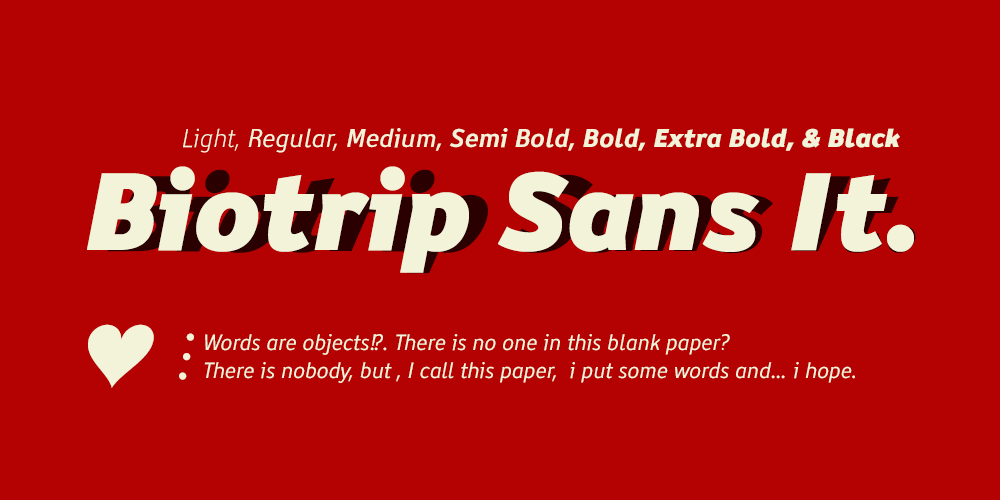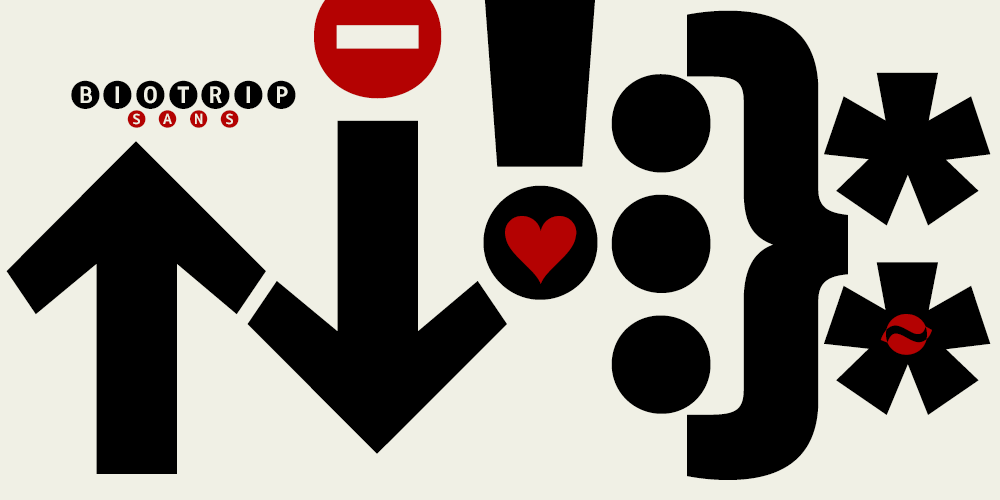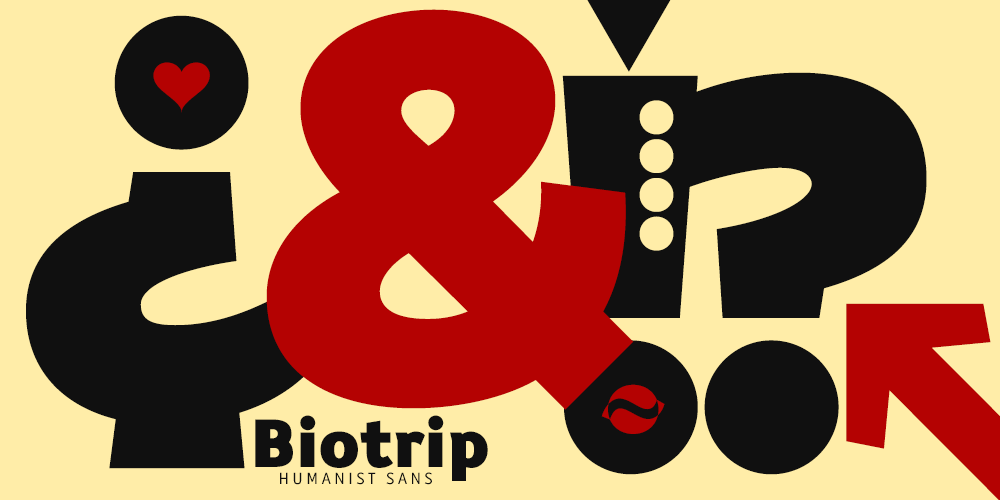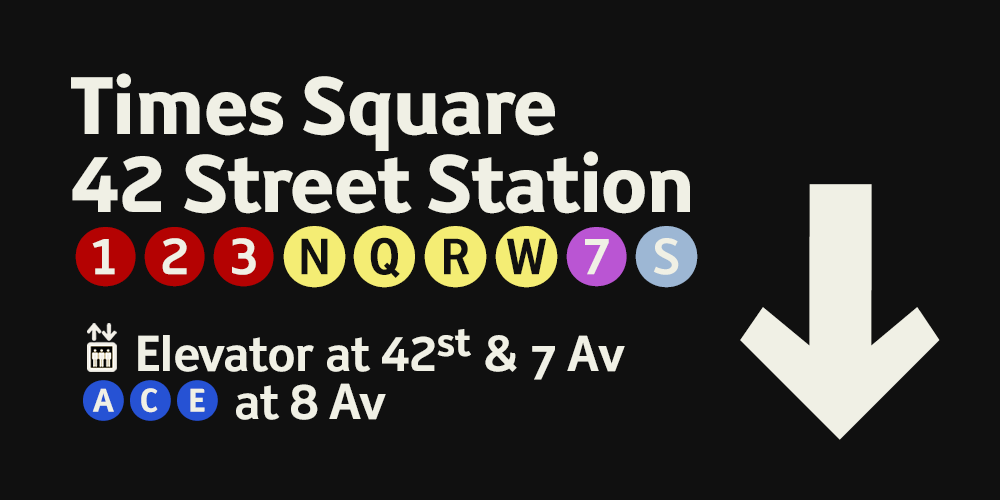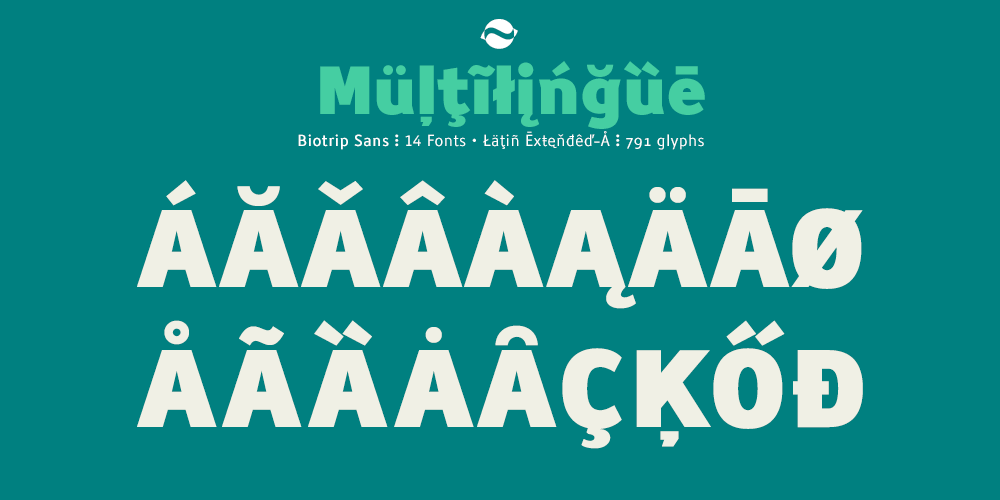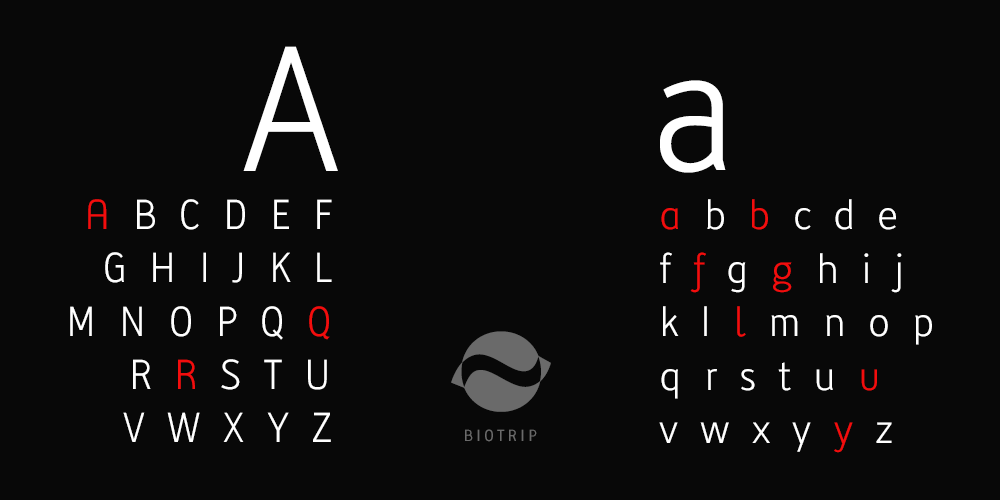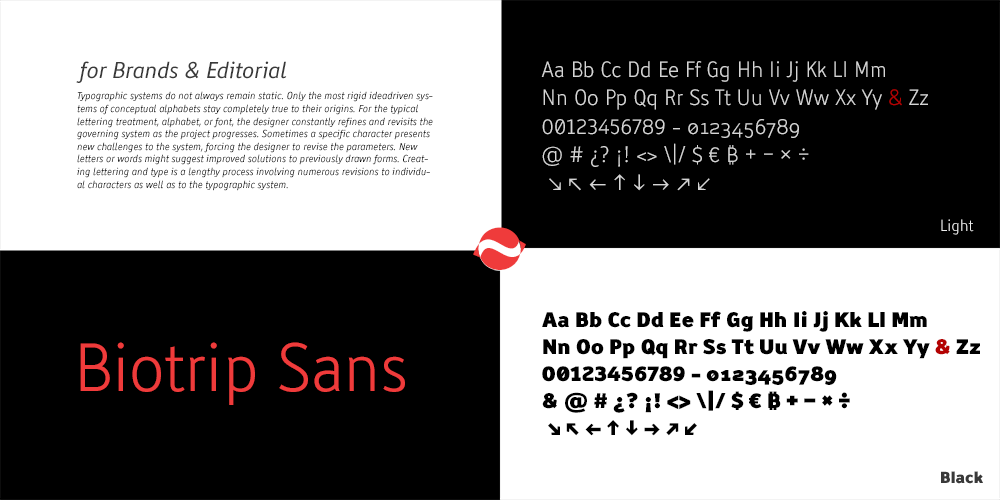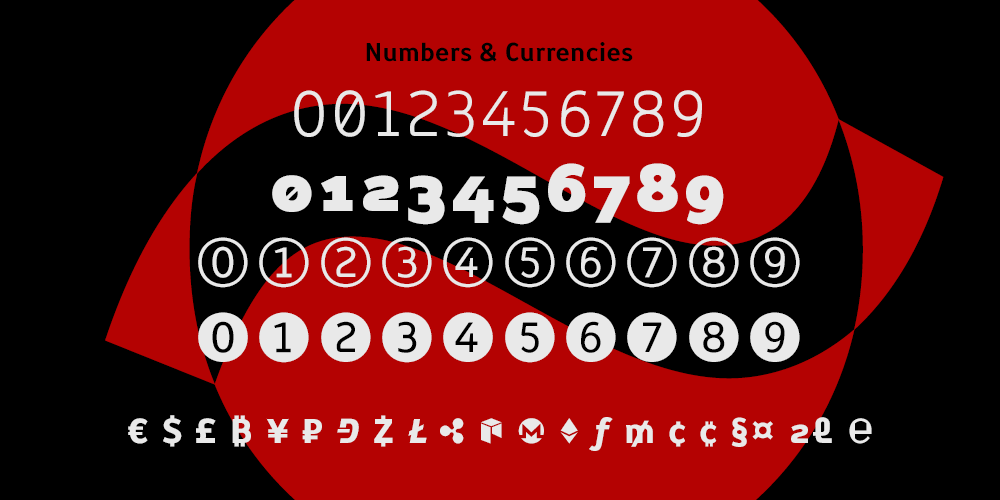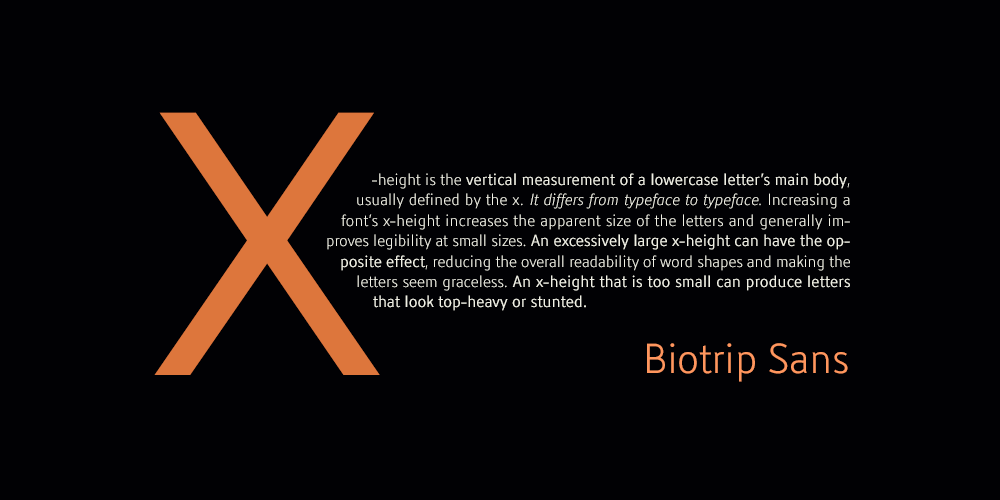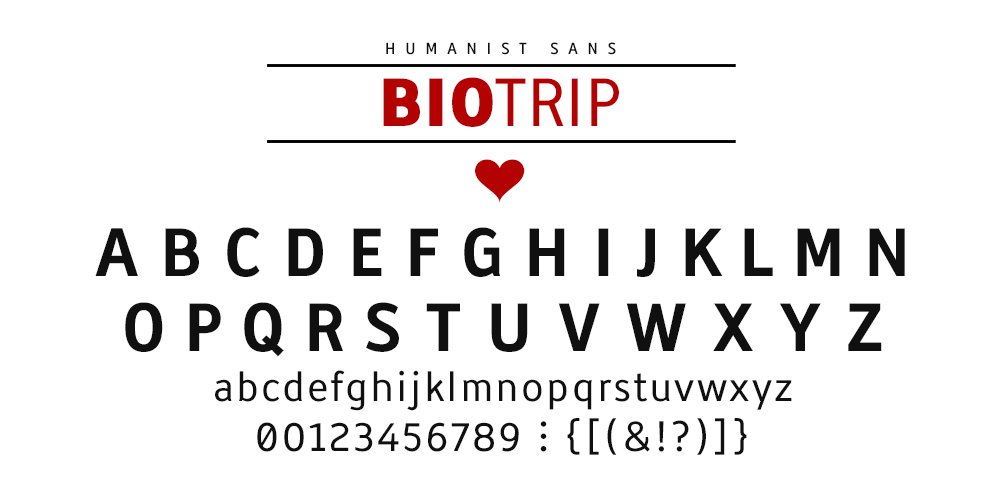
Estilo: Sans Serif, Display, Humanista, Editorial, Branding
Proporción: Light, Regular, Medium, Semi Bold, Bold, Extra Bold, Black
Glyphs: 791
Alternates: 189
Latin-Extended: Latín Básico, Europa Occidental, Central & Oriental.
Autor: deFharo
Versión: 1.791
Año de publicación: 2025.
Funciones OpenType: Additional languages, All Alternates, Alternate Annotation Forms, Bitcoin, Capital Spacing, Contextual Alternates, Denominators, Discretionary Ligatures, Fractions, Historical Forms, Inferiors, Kerning, Localized Forms, Numerators, Oldstyle Figures, Optical Size, Ordinals, Scientific Inferiors, Slashed Zero, Standard Ligatures, Stylistic Set, Subscript, Superior letters, Superiors, Superscript.
Regular & Italic | 791 glyphs | 14 fonts
Biotrip Sans — una tipografía que respira
He dado vida a una familia tipográfica amigable que es, ante todo, un viaje. Un viaje (Trip) desde la pureza de la geometría hacia la calidez de lo orgánico (Bio).
He diseñado Biotrip Sans desde ese punto de equilibrio imposible entre la razón y el impulso, entre la línea precisa del vector y el trazo impredecible de la mano. Es una sans humanista, una categoría que vive en ese fascinante borde donde lo geométrico se ablanda, donde las proporciones racionales ceden espacio a la humanidad del gesto. Aunque su estructura parte de la geometría, su espíritu es orgánico, vivo. No hay rigidez mecánica aquí, ni la frialdad de las fuentes grotescas. Cada curva fue pensada para ser vivida, no solo leída.
Biotrip Sans nace del trazo vivo, del impulso que une la mente al movimiento. Su estructura parte de la geometría, sí, pero cada forma fue suavizada por un pulso orgánico que hace que el ojo humano confíe, lea, respire. Las formas abiertas y neutrales y el ritmo equilibrado la convierten en una fuente cálida, versátil y naturalmente legible, incluso en los tamaños más pequeños —porque los buenos textos no deberían gritar para ser entendidos.
Una familia con vocación expansiva
Biotrip Sans se despliega en 14 fuentes metódicamente diseñadas, distribuidas en 2 estilos (Regular e Itálica genuina y fluida) y 7 pesos que van desde la elegancia etérea del Light hasta el impacto contundente del Black. Una familia grande, sí, pero no dispersa: cada peso comparte la misma tensión entre la estructura y la fluidez, entre la precisión tipográfica y la emoción manual.
He construido Biotrip Sans para ser una herramienta versátil y poderosa, con un sistema completo que te permitirá afrontar cualquier desafío de diseño con precisión y estilo. Y como toda familia sofisticada, Biotrip Sans trae un equipaje lleno de recursos:
- 6 juegos completos de números para adaptarse a cualquier contexto.
- 3 juegos de mayúsculas y 5 juegos de minúsculas para un control total del tono tipográfico.
- una colección de funciones OpenType que harían sonreír al tipógrafo más exigente: letras y números posicionales, fracciones dinámicas, fórmulas científicas, signos decorativos —del tricolon al asterism— para enriquecer el texto con sutileza y elegancia, anotaciones alternativas en estilos blackcircle y circlewhite, y ligaduras tanto estándar como discrecionales.
- Ah, y no olvidemos las flechas, los símbolos monetarios internacionales, e incluso las criptomonedas —porque el diseño contemporáneo no vive solo del euro ni del dólar.
- Soporte lingüístico Latin Extended-A que cubre una amplia gama de lenguas occidentales.
Biotrip Sans es una familia de fuentes multipropósito. Diseñada para moverse con soltura entre lo editorial, lo corporativo y lo experimental. Brilla en textos, encabezados, identidades visuales, carteles, empaques o como tipografía corporativa. Es una tipografía que puede susurrar o afirmar, pero nunca se queda muda. Biotrip Sans no busca parecer “perfecta”; busca parecer viva. No quiere ser otra sans más en tu carpeta de fuentes, sino un recordatorio de que incluso en la tipografía, la humanidad puede filtrarse entre las líneas rectas.
Biotrip Sans está diseñada para usos múltiples: Diseño Editorial (libros, revistas), Folletos y Cartelería, Identidad Corporativa y Logotipos, Packaging y Etiquetado, Señalización (su legibilidad es un activo invaluable). Su equilibrio entre racionalidad y humanidad la hace ideal para comunicar con claridad, sin perder cercanía ni personalidad.
En definitiva, Biotrip Sans es una experiencia tipográfica donde la geometría se suaviza, la legibilidad se eleva y el diseño se vuelve emoción. Bienvenidos!